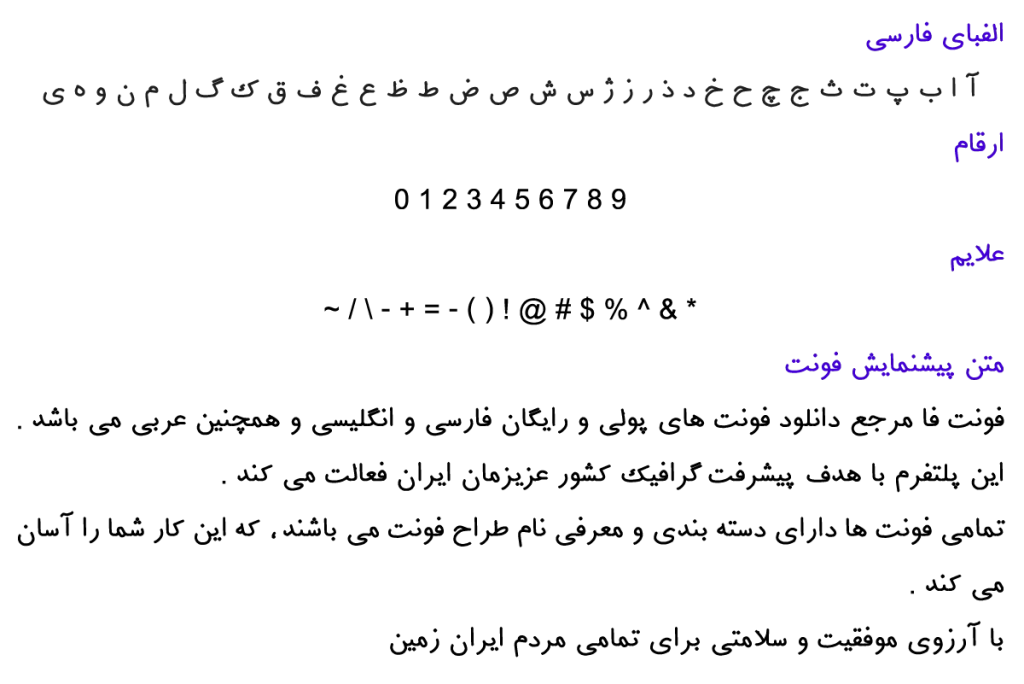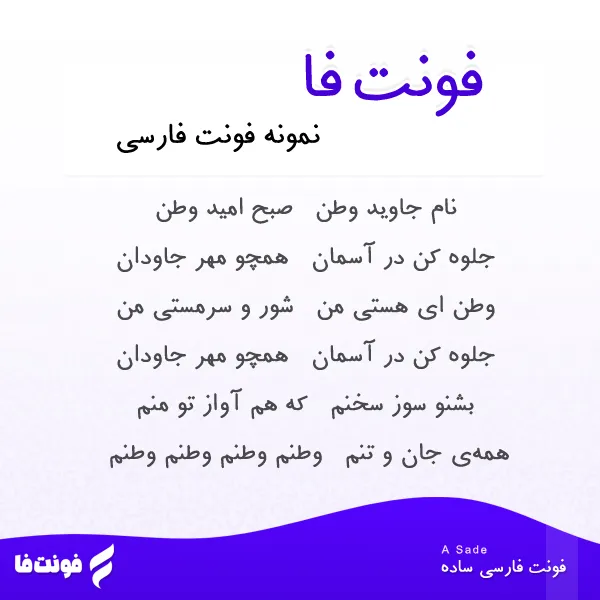
فونت فارسی ساده – A Sade
طراح فونت: مهدی صباغی نوع فونت: فونت دست نویس
توضیحات و معرفی فونت ساده
فونت فارسی ساده ( A Sade ) از مجموعه فونت های آزاد می باشد، همچنان نوع فونت دست نویس می باشد.
فونت شگفت انگیز و زیبای فوق توسط مهدی صباغی در سال 1393 طراحی و ساخته شده است.
تایپ فیس زیبای معرفی شده یکی از فونت های اتوکد می باشد که توسط طراح عزیز فارسی سازی شده است.
تصویر زیر، نمایی از این تایپ فیس را در قالب شعر «وطن» نشان میدهد.